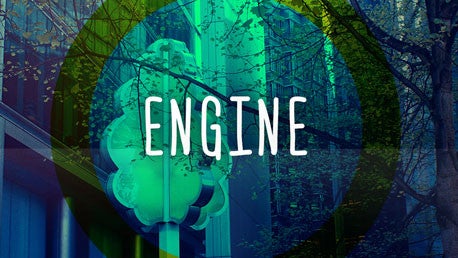
12 coole Handschrift-Fonts, die du noch heute benutzen kannst
Handschrift ist nicht gleich Handschrift und beschränkt sich nicht nur auf Kalligraphie. Wir haben einige coole handschriftliche Fonts für dich zusammengestellt.
Engine Font
Wenn wir über handschriftliche Fonts sprechen, sind nicht zwangsläufig kalligraphische Meisterwerke gesucht. Es gibt viele Möglichkeiten, einen Font nach einer Handschrift aussehen zu lassen. In letzter Zeit stolpert man immer häufiger über derartige Fonts – sowohl im Print- als auch im digitalen Bereich. Einige kostenlose Handschrift-Fonts, haben wir hier für dich zusammengestellt.
LeHand
LeHand ist der erste Font von Idieferdie. Der Font kommt als verspielte Handschrift daher und eignet sich gut für verschiedenste Design-Experimente.
Yore
Yore wirkt auf den ersten Blick wie eine klassische Handschrift. Bei genauerem Hinsehen fallen aber die feinen Elemente, die Designer Poem haiku in die feine Schrift eingearbeitet hat, auf. Yore ist ein verspielter und doch traditionell anmutender Font, der sich durchaus für das ein oder andere Branding eignen könnte.
Whatever It Takes
„Whatever it takes“ nimmt uns zurück in die Schulzeit und erinnert an Kreide auf einer Tafel. Der Font ist für den nicht kommerziellen Einsatz kostenlos. Für kommerzielle Benutzung des Font bittet der Designer um eine Spende von fünf US-Dollar.
Before Breakfast
Before Breakfast ist eine Schrift von Simon Stanford und entstand mit Hilfe des iFontMaker für das iPad. Das besondere: Der Designer setzte sich ein Limit von zehn Minuten für die Erstellung des Fonts. Das Ergebnis: Ein lockerer Font, der „wahrscheinlich gegen alle Regeln der Typographie verstößt“ und den Namen Before Breakfast wirklich verdient hat.
Engine
Die von Ferdie Balderas designte Font-Engine steht im Regular- und Italic-Schriftschnitt mit Klein- und Großbuchstaben zur Verfügung und unterstützt neben Englisch eine Reihe zusätzlicher Sprachen: Darunter Französisch, Polnisch, Türkisch und Russisch.
Chomp
Chomp ist ein verspielter Font von Designer William Bayley Suckling. Die Schriftart ist für persönliche und kommerzielle Projekte frei verfügbar.
Haiku’s Script
Haiku’s Script ist Poem Haiku’s erster Versuch, einen Font zu designen. Die Arbeiten an der für persönliche Zwecke kostenlosen Schrift begannen im Jahr 2011 und nahmen drei Monate in Anspruch.
Pops
Der New Yorker Designer Sune Madras kreierte mit Pops eine Schriftart, die der Handschrift seines Vaters entsprechen sollte, die er normalerweise für kurze Nachrichten und Überschriften benutzte. Ein sehr gelungener und persönlicher Font.
Sketch Block
Sketch Block ist eine für Headlines vorgesehene Schriftart von Lukas Bischoff. Bischoff designte den Font komplett auf Papier und digitalisierte ihn anschließend, um so eine besonders persönliche und realistische Note einzubauen.
Journal
Journal ist eine kostenlose Schrift von Hans Gerhard Meier, deren Name bereits verrät, für welche Einsatzzwecke sie gestaltet wurde.
Mari & David
Mari & David ist ein kostenloser Font von Rodrigo German. Die Schrift erinnert an dicke Filzstifte auf dünnem Papier und ist in den Schriftschnitten regular, bold und extrahold verfügbar. Das ermöglicht viele spannende Kombinationen.
Bispo
Der brasilianische Typograph Jackson Alves wollte einen Font kreieren, der jedem die Möglichkeit gibt, etwas charmantes zu erschaffen und dabei die Vorteile der Opentype-Features zu nutzen. Das Ergebnis in Form des Script-Font Bispo, kann sich definitiv sehen lassen.